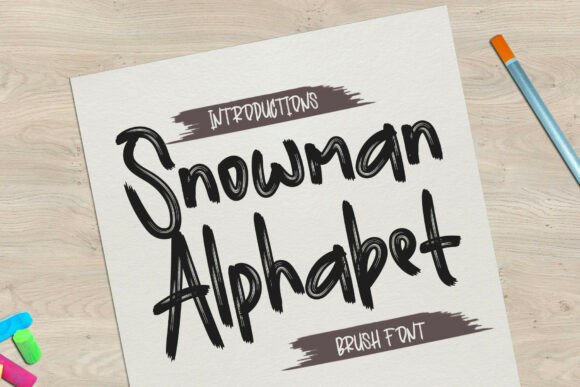
Snowman Alphabet
適切なデザイン要素を見つけるのは難しい場合がありますが、Snowman Alphabetは作品を即座に引き立てる優れたコレクションを提供します。
POD(オンデマンド印刷)製品、結婚式の招待状、またはソーシャルメディアのグラフィックを作成している場合でも、Snowman Alphabetは理想的です。